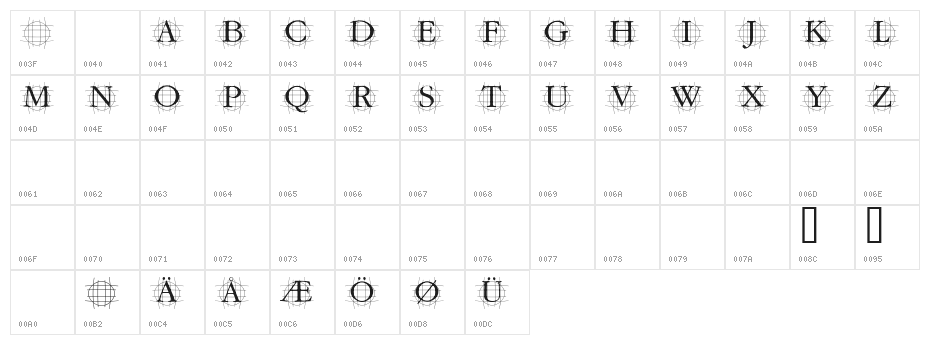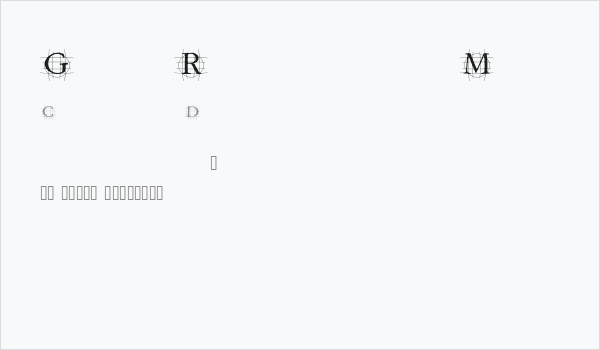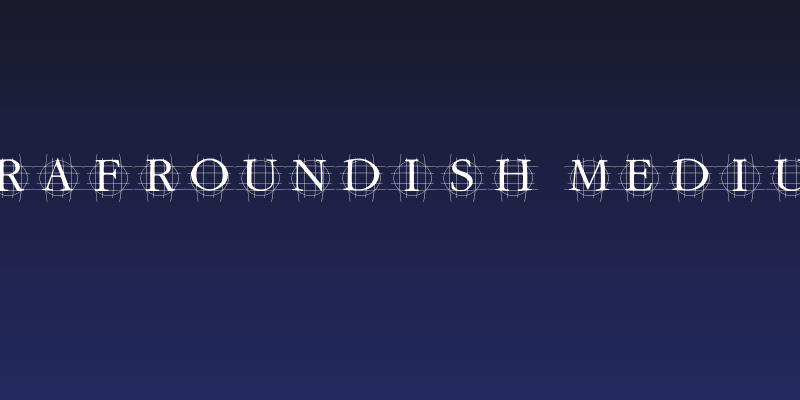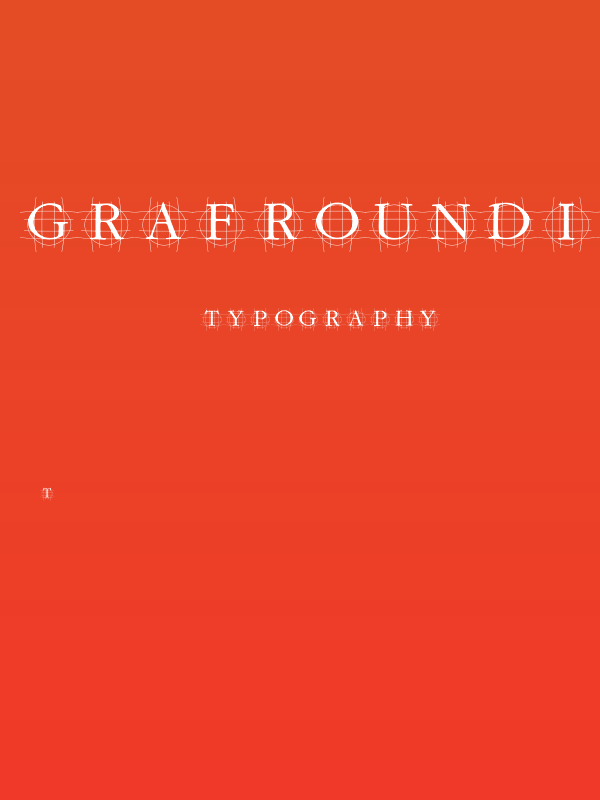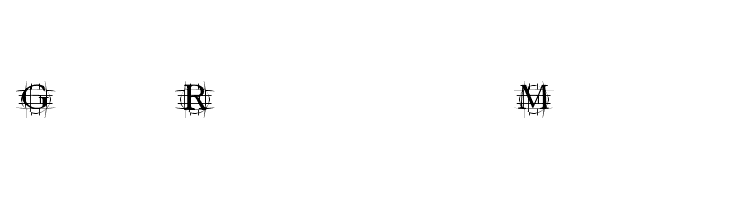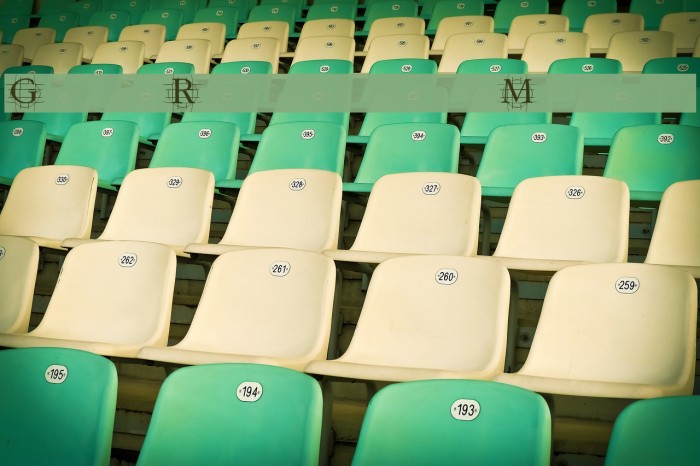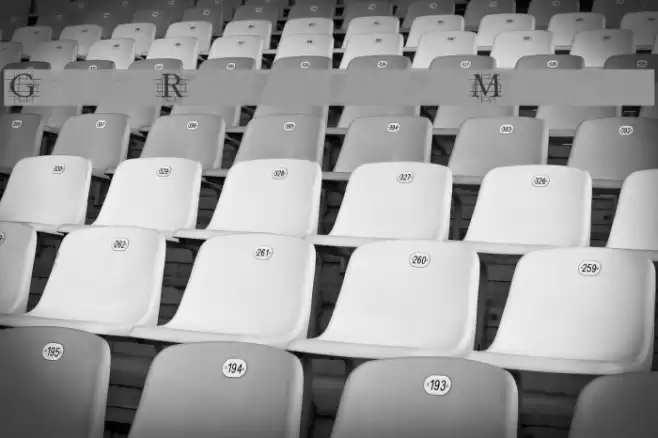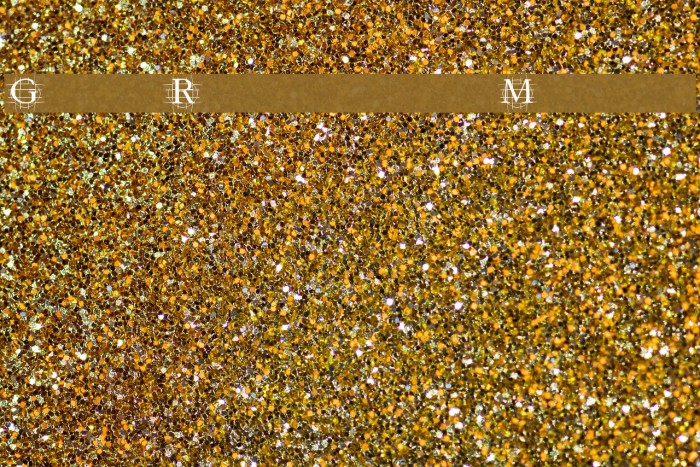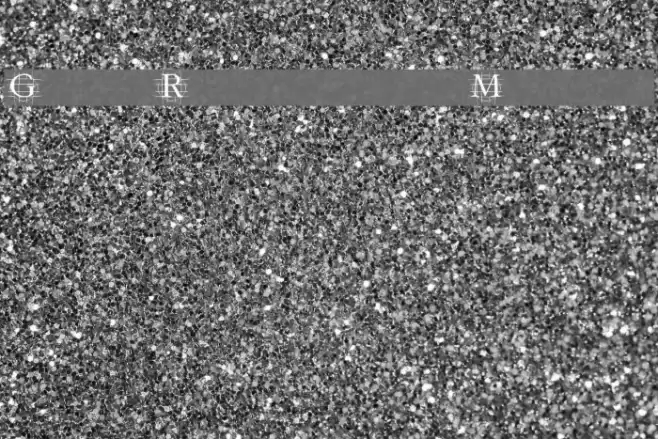
GrafRoundish Medium Font
| समग्र शैली | Decorative |
| उपयोग का मामला | Logos, Posters, Artistic Branding |
| सुझाए गए प्रोजेक्ट | Ideal for creative projects such as art posters, album covers, or branding for artistic ventures. |